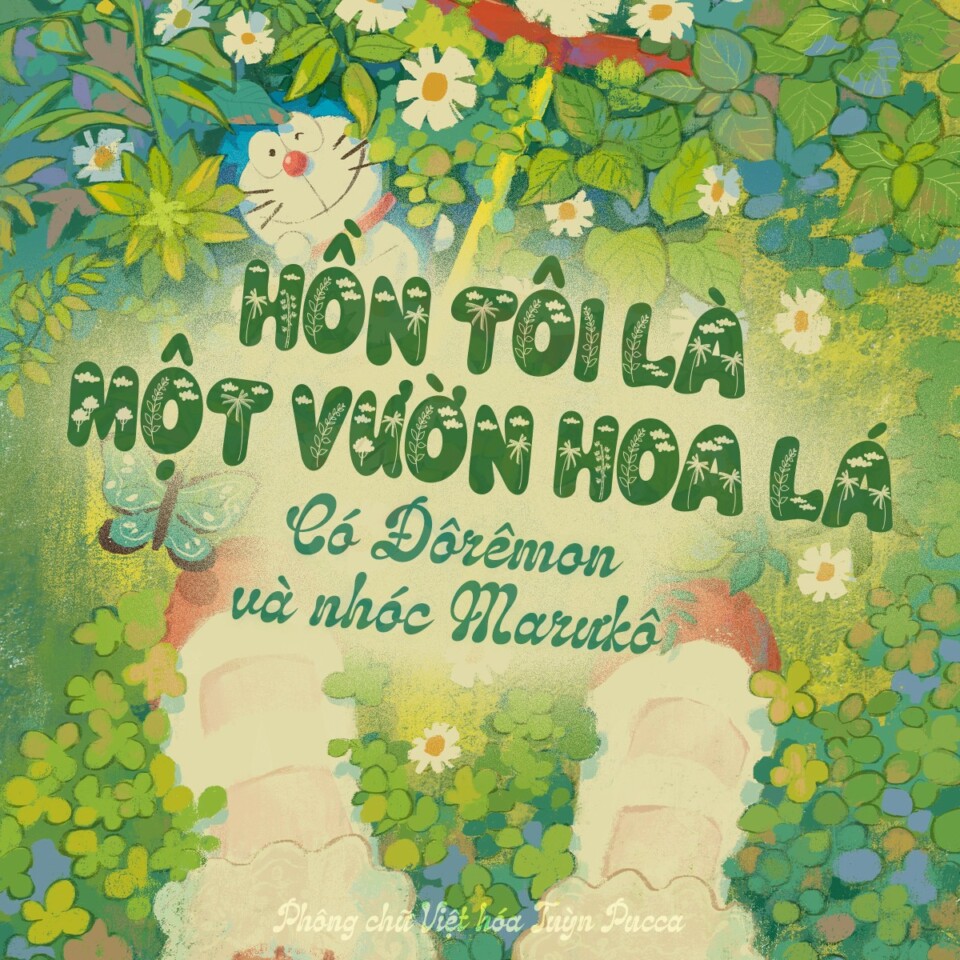
Font Việt hóa TP Earth Days Swash
Font Việt hóa TP Earth Days Swash – Bộ Font Chữ Nghệ Thuật Cho Thiết Kế Xanh
Giới thiệu về Font Việt hóa TP Earth Days Swash
Trong thế giới đồ họa hiện đại, việc tìm kiếm một mẫu Font Miễn Phí có phong cách mềm mại và gần gũi với thiên nhiên là ưu tiên hàng đầu của nhiều nhà thiết kế. Font Việt hóa TP Earth Days Swash chính là lựa chọn hoàn hảo để truyền tải thông điệp bảo vệ môi trường và sự bền vững. Đây là phiên bản mở rộng của bộ phông chữ Earth Days nổi tiếng, được bổ sung thêm các đường nét uốn lượn (swash) điệu đà, tạo nên vẻ ngoài thanh thoát nhưng không kém phần mạnh mẽ. Với bản việt hóa chỉn chu, người dùng có thể dễ dàng sử dụng trong các phần mềm thiết kế chuyên nghiệp mà không lo lỗi gõ dấu tiếng Việt.
Đặc điểm nổi bật của bộ font chữ này
Điểm thu hút nhất của Font Việt hóa TP Earth Days Swash nằm ở các ký tự thay thế đầy tính nghệ thuật. Những nét chữ được mô phỏng theo hình dáng của cành cây, ngọn cỏ, mang lại cảm giác hữu cơ và sống động. Bộ font này cực kỳ phù hợp cho các dự án thiết kế logo, poster sự kiện Ngày Trái Đất, hoặc các ấn phẩm truyền thông cho trường học. Sự kết hợp giữa nét chữ đậm và các chi tiết bay bổng giúp nội dung văn bản trở nên nổi bật, thu hút ánh nhìn của người xem ngay từ lần đầu tiên.
Cách ứng dụng Font Việt hóa TP Earth Days Swash hiệu quả